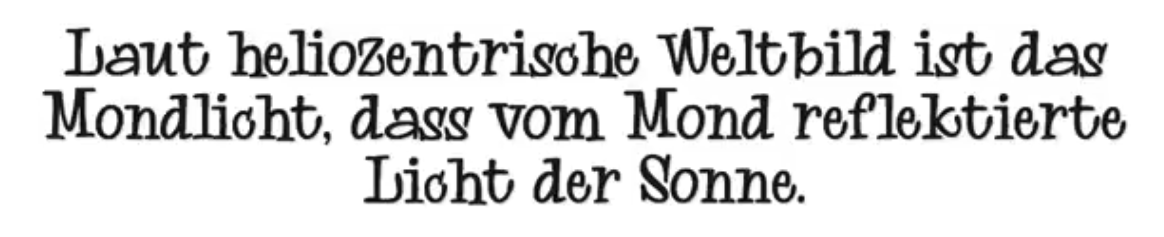
Name und Informationen zu einer Folkwell-Schrift (Slabserif, Marker, Handgemacht) gesucht
ich suche den Namen und weitere Informationen zu diese mir vollkommen unbekannte Folkwell-Schrift.
Die Schrift sieht aus wie eine der typischen Folkwell-Schriften vom Type Marker. Es ist aber keine Apache/Jester, Canned Corn, Idolwild. Ich stehe da total auf dem Schlauch und die verschiedenen Suchmaschinen (Whatthefont, WhatFontis  ... ) brachten auch keine Ergebnisse. Kennt einer der hier An- und Verwesenden zufälligerweise diese Schrift?
0 Whoa DNA (Regular)
Dazu kommen dann noch weitere Verzeichnisse ganz oben. Softmaker mit den vielen von Softmaker verteilten Schriften, Corel mit den so verteilten Bitstreamschriften, System mit den Schriften die mit Betriebssystemen von Mikrosoft, IBM und Apple verteilt wurden sowie Printer, mit den Schriften die bei verschiedenen Druckern früher mal dabei waren. Diese Sammlungen sind zur Dokumentation und dienen fast nur noch der Recherche. Woher kam die Schrift die damals verwendet wurde? Software wie Office? Betriebssystem? Oder war die beim damals benutzen Drucker dabei? Was gibt es da als Ersatz? Da sind auch nicht immer die Schriften enthalten, des öfteren nur Beispielbilder und Angaben zur Schrift oder Listen (Text, PDF ...) Allerdings sind in der eigentliche Sammlung sehr häufig Einträge unter dem Schlüsselwort Alternates, die auf diese Schriften verweisen oder Textangaben zu diesen Schriften in den Textdateien. Dadurch bin ich mit etwas Glück in der Lage bei einer einmal gefundenen Schrift weitere Erscheinungsformen zu finden.
Das ganze System ist in rund 20 Jahren gewachsen. Zuerst lief das alles auf OS/2 mit REXX (daher kommt noch das Erbe des Dateinamen descript.ion von einem über 20 Jahre alten Skript, das ich für meine Zwecke adaptiert habe) und nun auf Linux mit bash und pearl. Über den ganzen Datenbestand rennt dann vor jeder Archvierung ein Index-Skript. Das sieht nach unverpackten Dateien oder Archiven und entpackt diese, liest dann die Daten der Schriften aus, schreibt eine fette Textdatei mit Schriftnamen und Dateinamen zum Suchen. Dazu wird dann noch der HTML-Index angelegt und am Ende eine md5sum für das Überprüfen von evtl. erzeugten Datenträgern (DVD).